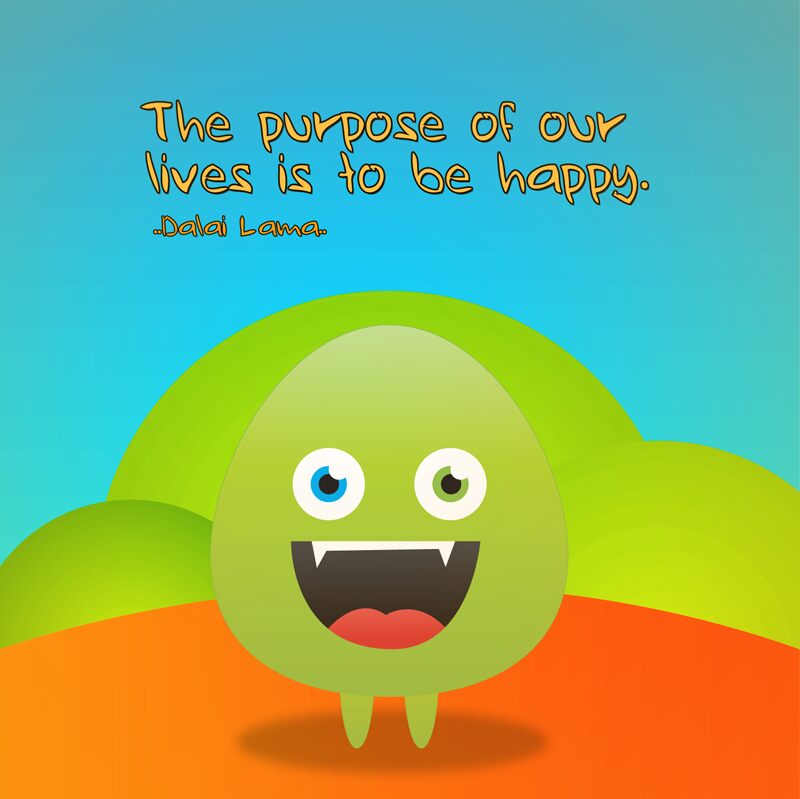
<p>Ugly Hand Writing to lekki krój pisma imitujący pismo odręczne, który emanuje niekonwencjonalnym urokiem. Autorem tego projektu jest Cenz Qobbal. Krój ten oddaje istotę surowej i nieskrępowanej ekspresji, przywodząc na myśl szybkie notatki i osobiste zapiski. Jego nieregularność i „niedoskonałości” wyróżniają go na tle innych, czyniąc go doskonałym wyborem dla projektów, które chcą przyciągnąć uwagę autentycznością.</p><p>Estetyka Ugly Hand Writing opiera się na umiejętności przekazywania osobowości i spontaniczności. Pozornie przypadkowe pociągnięcia sugerują śmiałość, dając projektantom możliwość nadania pracy wyrazistego charakteru. Niezależnie od tego, czy chodzi o sugestywny branding, przyciągającą wzrok grafikę do mediów społecznościowych czy nieformalną komunikację, styl tego pisma jest na tyle wszechstronny, że dodaje głębi wielu kreatywnym realizacjom.</p><p>Przyjmując doskonale niedoskonałą naturę ludzkiego pisma, Ugly Hand Writing staje się czymś więcej niż tylko fontem – staje się wyrazem artystycznym, który celebruje indywidualność w projektowaniu.</p><p>Darmowy do użytku osobistego; w przypadku wykorzystania komercyjnego wymagana jest darowizna.</p>